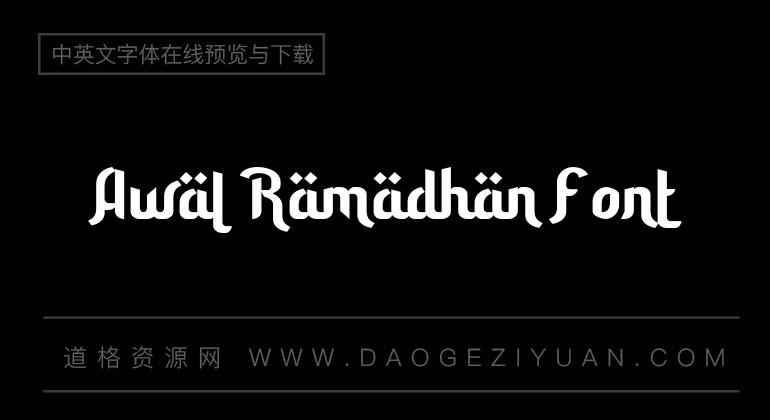
Awal Ramadhan Font 是一种由 Tama Putra 设计的手写风格字体,主要用于 Ramadan(伊斯兰教的斋月)的设计。它的特点是手写风格,字母间距较小,线条柔和,风格简洁明了。该字体包括大小写字母、数字和常用标点符号,可以用于印刷、海报、广告、包装等设计领域。Awal Ramadhan Font 的设计灵感来自于阿拉伯语书法和印度尼西亚文化元素,非常适合用于与伊斯兰教有关的设计项目。内容介绍
Awal Ramadhan Font是一款非常不错的手写艺术字体,具有很好的视觉感,适合于文化类的宣传设计、商业类品牌的广告和产品包装设计以及个性化文字排版等较多场景。